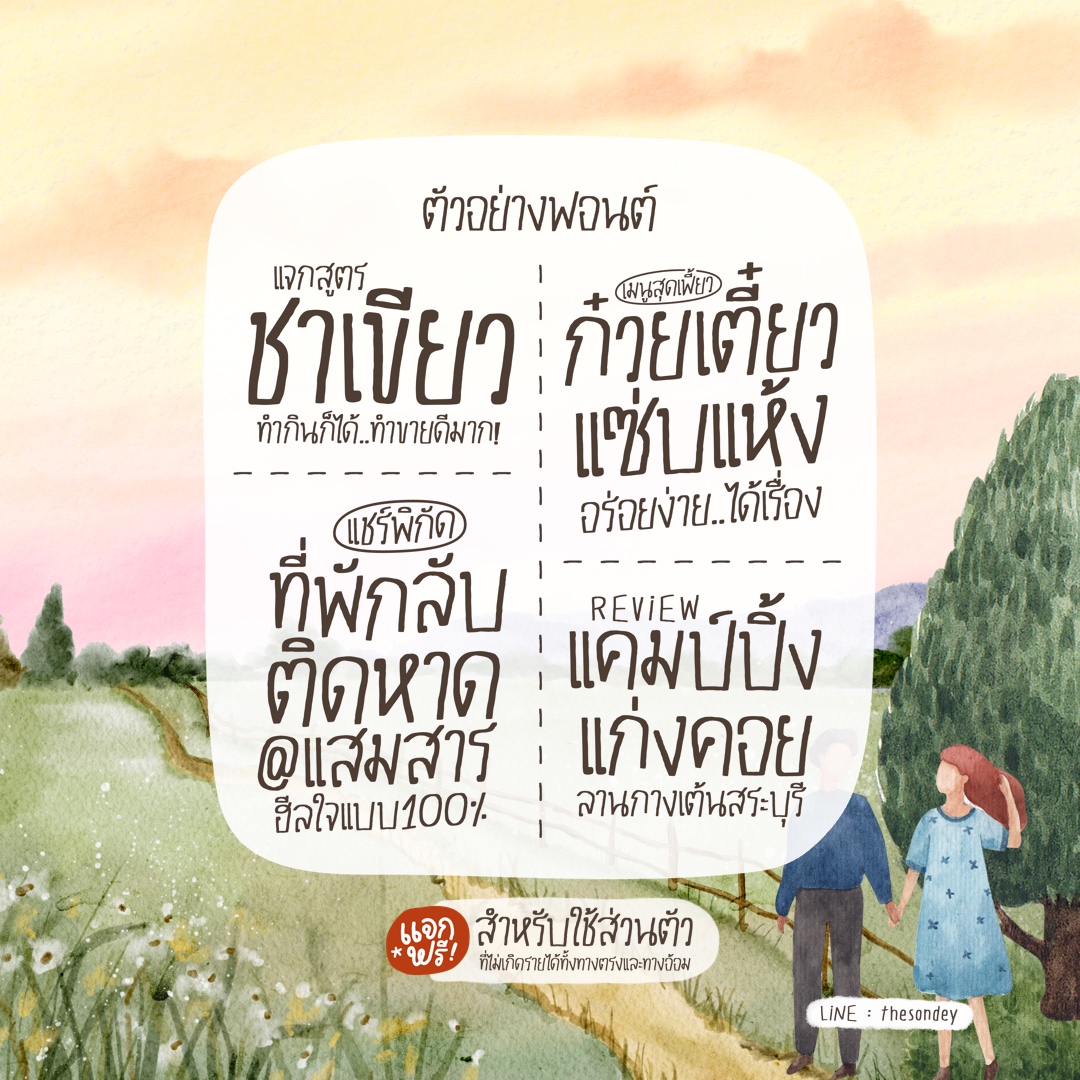
ชื่อฟอนต์ : นายช่าง2468
ฟอนต์นายช่าง2468 ต้นทางจากอักษรของสมเด็จครูที่พบในพิมพ์เขียวงานสถาปัตย์ เมื่อประมาณร้อยปีที่แล้ว ร่างเส้นขึ้นมาใหม่ ชอบความมีเส้นบรรทัดเลยเติมเข้าไปด้วย ใช้เป็นข้อความ หากอยากได้พาดหัวให้กด bold
อยากให้ดูเพิ่มเติมที่ e-book งานออกแบบสถาปัตยกรรมไทย ฝีพระหัตถ์สมเด็จพระเจ้าบรมวงศ์เธอ เจ้าฟ้ากรมพระยานริศรานุวัดติวงศ์ https://asa.or.th/handbook/the-architectural-works-of-prince-narisararuvattiwongse-a-transition-of-thai-architecuture/
ฟอนต์พาร์มิเย่ (TCS4Palmier)
ฟอนต์ไม่มีหัวบรัชแบน
น้ำหนักเส้นไม่ค่อยเท่ากัน
ทำให้ชิ้นงานดูไม่น่าเบื่อ
ฟอนต์ 331PANI.ส้มตำ
ฟอนต์แซ่บๆ จะใช้แบบรายละเอียด
หรือใช้เป็นหัวข้อ ใช้ทำคลิป
แต่งภาพ,Goodnoteได้หมด
ฟอนต์มี 3 ไฟล์ - น้ำหนัก บาง ปกติ หนา
ฟอนต์ดังโงะ (TCS4Dango)
ฟอนต์สไตล์นี้ แต่งรูปเป็นธรรมชาติมาก
ทำปกคลิปก็ปัง จดโน๊ต ตั้งฟอนต์เครื่องได้
ภายในไฟล์จะได้รับฟอนต์ 3 ขนาด บาง ปกติ หนา น้ำหนักเท่ากันพร้อมปรับสระเรียบร้อยพร้อมใช้งานทุกแอปพลิเคชั่น